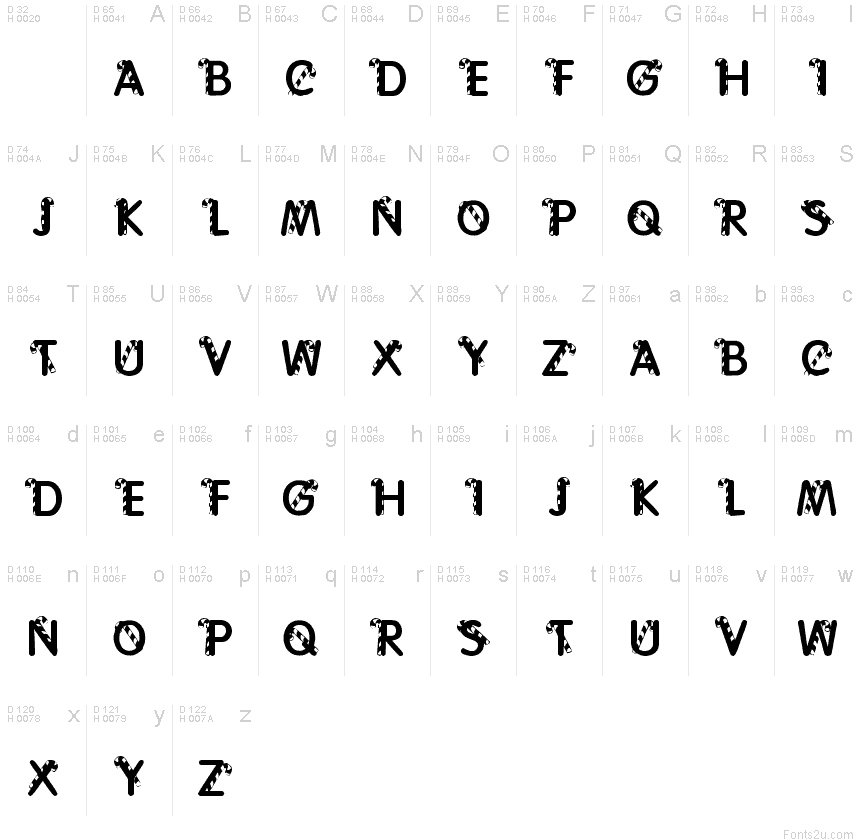
Písmo KR Cane Letters od Kat je dekorativní font zdarma, který promění každé slovo v pruhovanou vánoční hůlku. Výrazné, zaoblené tahy jsou obepnuty ostrými diagonálními pruhy, takže i krátké nadpisy působí sladce a svátečně. Písmena jsou dostatečně robustní pro rychlé čtení, ale stále si zachovávají ten ručně kreslený, řemeslný půvab, který znáte z papírových dekorací nebo vánočních výloh.
S KR Cane Letters můžete rychle vyzdobit vánoční přání, plakáty na zimní festivaly, pozvánky na dětské oslavy, pracovní listy, nástěnky a veselé grafiky na sociální sítě. Tento font zdarma vynikne ve velkých velikostech, kde pruhy opravdu zazáří. V hlavním textu jej kombinujte s čistým bezpatkovým písmem, nechte KR Cane Letters, ať se postará o sváteční atmosféru, zatímco zbytek textu zůstane přehledný a čitelný.